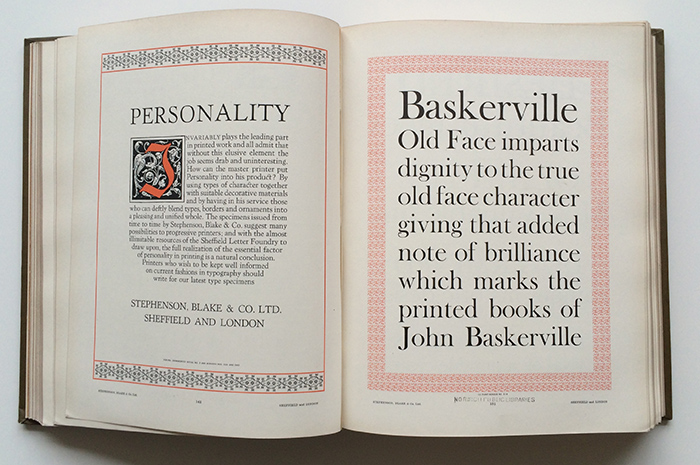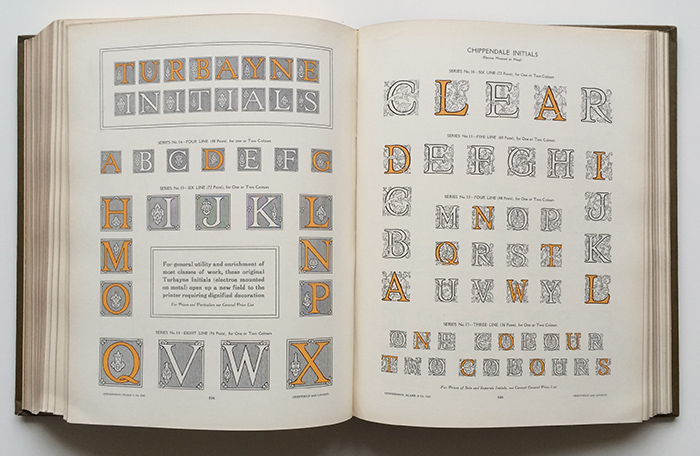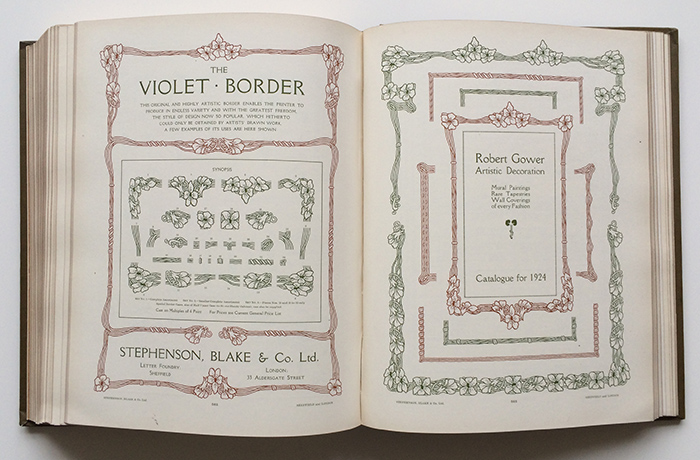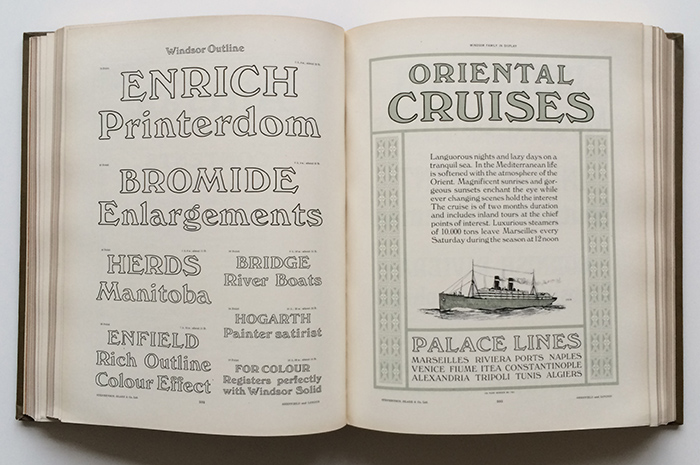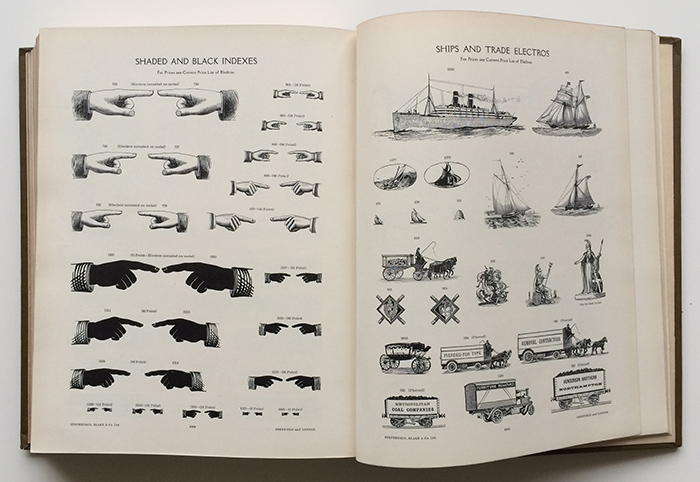
Stephenson Blake & Co war eine britische Schriftgießerei aus Sheffield, die vom 19. Jahrhundert bis in die 1990er-Jahre aktiv war. Sie gilt als die letzte aktive britische Bleisatzschriftgießerei. Die Materialen der Gießerei befinden sich heute im Type Museum, London.
Dieser Eintrag bezieht sich auf die Hauptprobe der Gießerei aus dem Jahr 1924.
Untertitel: Stephenson, Blake & Co.
Autor(en): Stephenson, Blake & Co.
veröffentlicht: 1924
Verlag: Stephenson, Blake & Co. LTD.